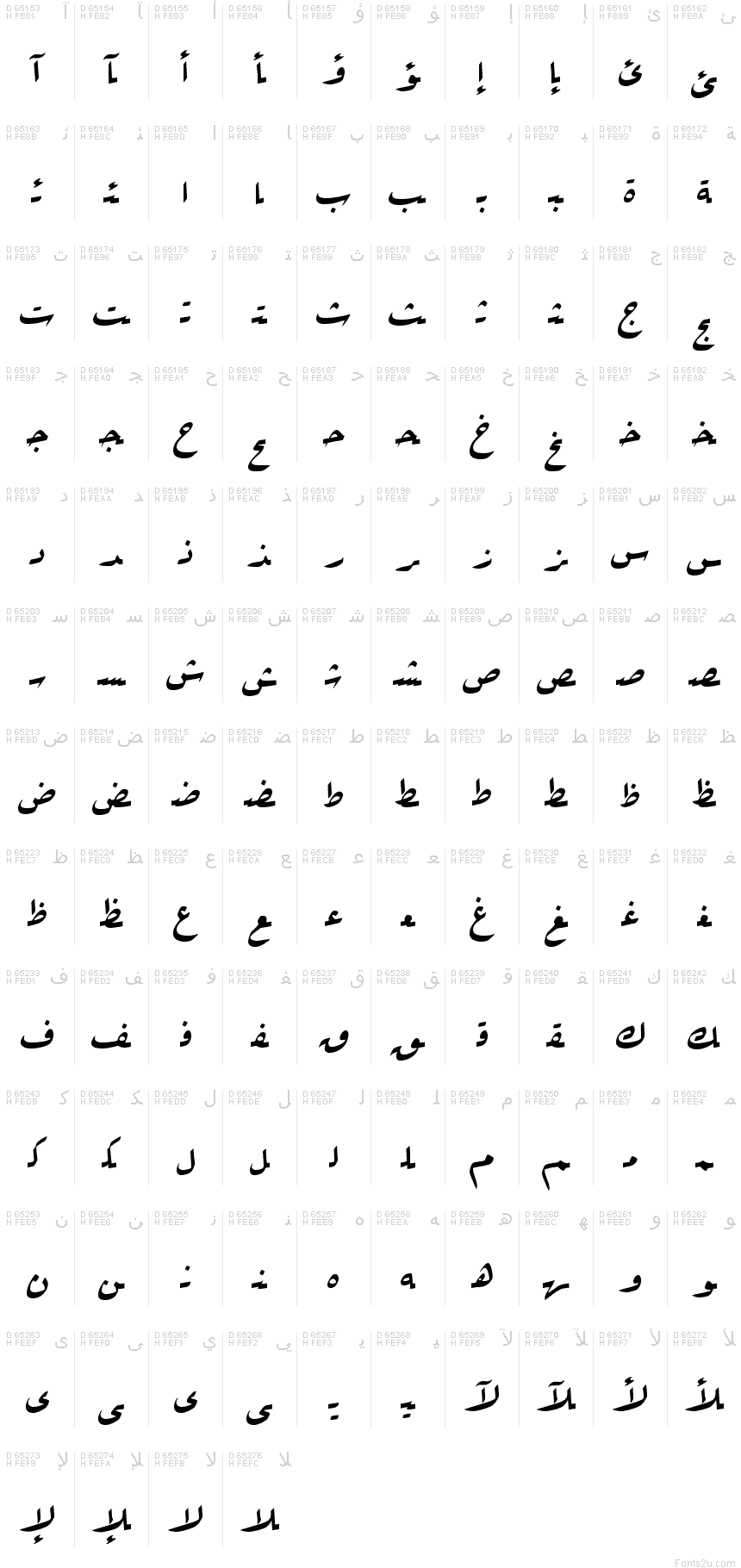
B Arabic Style od Borna Rayaneh to darmowy arabski krój typu display o wyrazistym, kaligraficznym rytmie. Litery są zwarte i płynne, a pociągnięcia linii przechodzą w zaokrąglone łuki i ostre zakończenia, co nadaje krojowi żywy, ręcznie kreślony charakter, daleki od sztywnej geometrii.
Dzięki temu idealnie sprawdzi się na plakatach kulturalnych, w identyfikacji wizualnej restauracji, na okładkach płyt, ulotkach i w krótkich nagłówkach, gdzie darmowy krój z mocnym arabskim akcentem pozwala błyskawicznie nadać ton. Wykorzystaj go w tytułach, na okładkach lub w krótkich logotypach, gdy chcesz, by same litery wnosiły dynamikę i dekoracyjność.